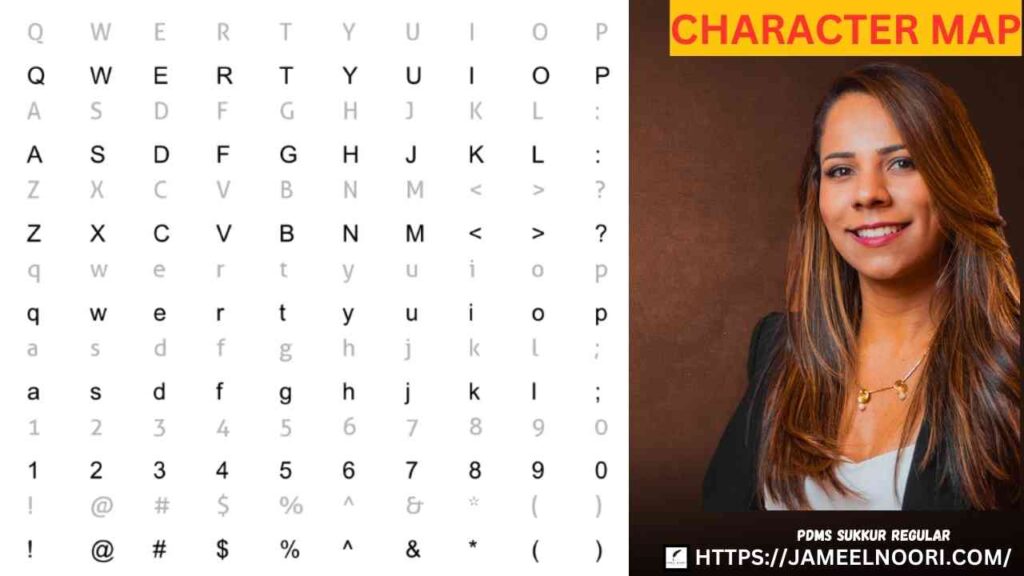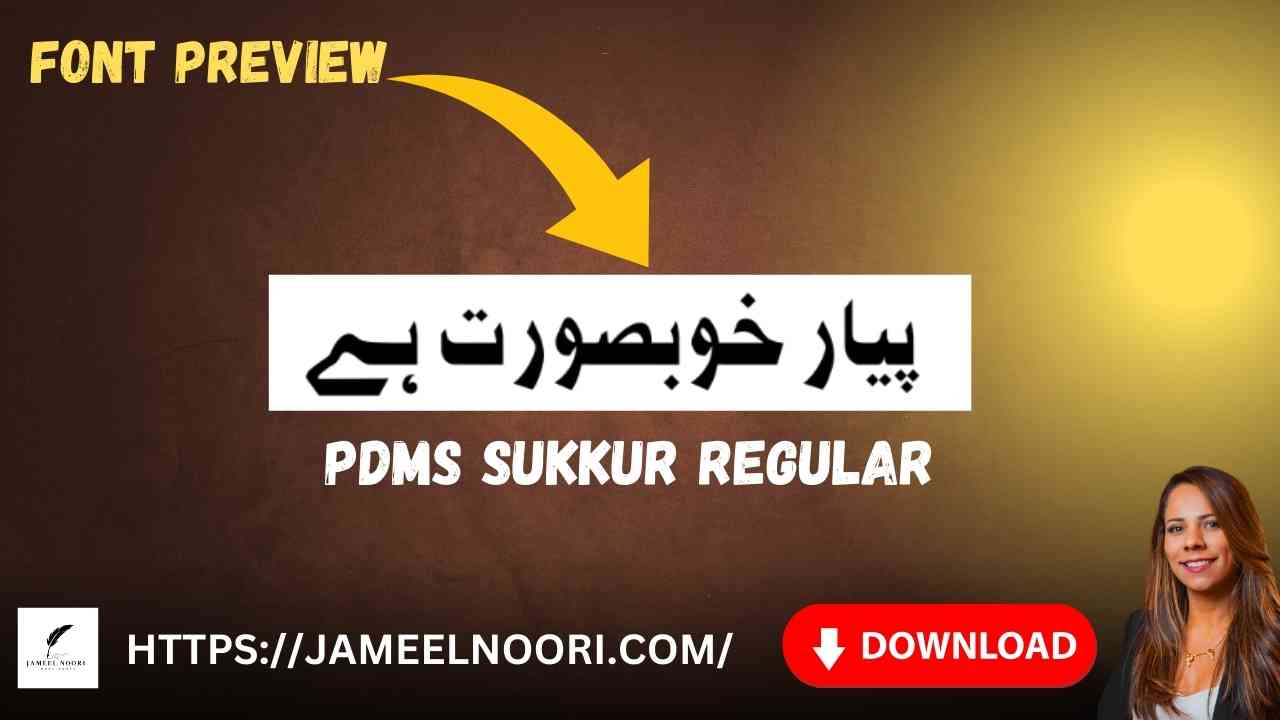
Introduction to Download Urdu font PDMS Sukkur Regular
Aaj ke digital daur me Urdu fonts ki demand bohot zyada barh gayi hai. Har designer, writer aur student chahata hai ke wo apne documents, presentations aur design projects me stylish aur readable Urdu font use kare. Download Urdu font PDMS Sukkur Regular unhi fonts me se aik hai jo apni simplicity aur readability ki wajah se popular hai. Is font ka design clean aur balanced hai, jo chhoti aur badi screen dono par equally readable hota hai.
Features of Download Urdu font PDMS Sukkur Regular
PDMS Sukkur Regular ek Regular TrueType Font hai jo different platforms ke sath compatible hai. Iske kuch major features ye hain:
- Simple aur clear design jo documents ko professional look deta hai.
- Urdu aur Sindhi typing dono ke liye suitable.
Benefits of Using Download Urdu font PDMS Sukkur Regular
Is font ke use karne ke bohot faide hain:
- Readable Urdu Documents – Aapke documents aur books professional lagti hain.
- Graphic Designing ke liye Perfect – Posters, flyers aur banners me yeh font stylish touch deta hai.
- Website Content me Behtareen – Agar aap Urdu blogging ya online publishing karte hain, to yeh font highly recommended hai.
Bullet Points: Why Choose PDMS Sukkur Regular?
- Professional aur modern look.
- Suitable for Urdu, Sindhi aur other regional scripts.
Conclusion on Download Urdu font PDMS Sukkur Regular
Agar aap Urdu typing ke liye reliable aur professional font dhund rahe hain to Download Urdu font PDMS Sukkur Regular aapke liye best choice hai. Iski readability, free availability aur compatibility isay Pakistan ke designers aur writers ke liye ultimate solution banati hai. Abhi is font ko download karein aur apne documents aur designs ko aur bhi attractive banayein.
Does this font support Urdu typing only?
No, it also supports Sindhi and some other regional scripts.